«Никак не пойму, зачем делать незаметные шрифты»
«Галина Банникова и ее шрифты» — выставка, посвященная не только работам, но и основным принципам создания шрифта Галины Банниковой, советской художницы и типографа. Каталог выставки представляет собой исследовательское эссе о методе работы Банниковой, где текст подкрепляется эскизами, производственными материалами и набросками.
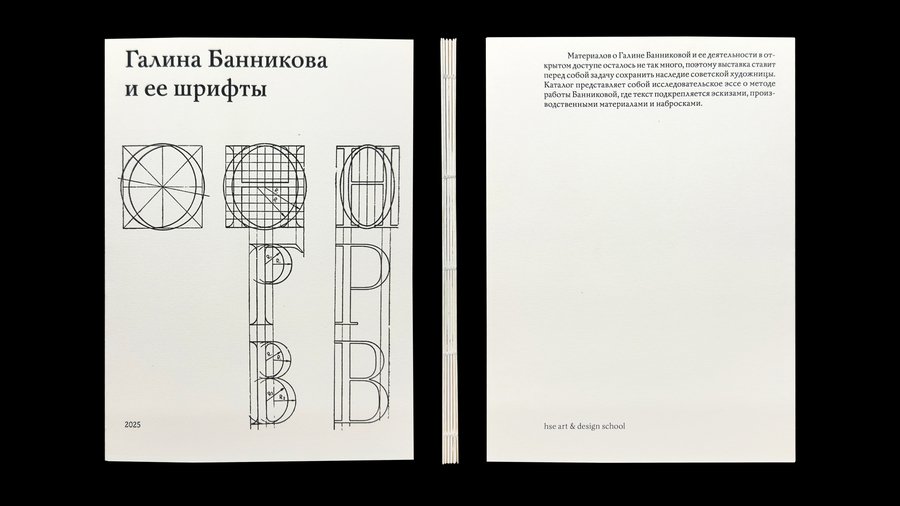
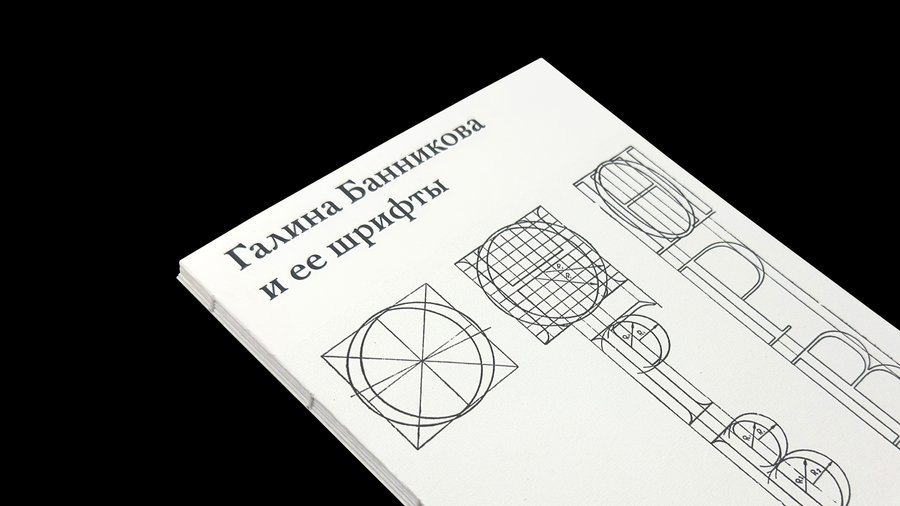
Первый раздел каталога посвящен гарнитурам-предшественникам Банниковской — именно их художница изучала и анализировала для того чтобы в дальнейшем применить схожие техники в своем шрифте.
Наиболее известной работой художницы стала названная ее фамилией Банниковская гарнитура — шрифт, выпущенный в 1949 году сначала для ручного, а в 1951-м и для строкоотливного набора. Является первым оригинальны кириллическим шрифтом антиквенного типа, предназначенный для набора художественной литературы.
Второй важный проект Банниковой — гарнитура Байконур, опыт создания книжной антиквы нового стиля. Главное препятствие, с которым она столкнулась, состояло в высоком контрасте подобных антикв, который снижал их удобочитаемость в мелком кегле при наборе больших массивов текста. Третий шрифт Банниковой — гарнитура Кама, акцидентный гротеск. Рисунок Камы — открытый и живой, в знаках этого шрифта преобладают мягкие, пластичные формы с округлыми завершениями.